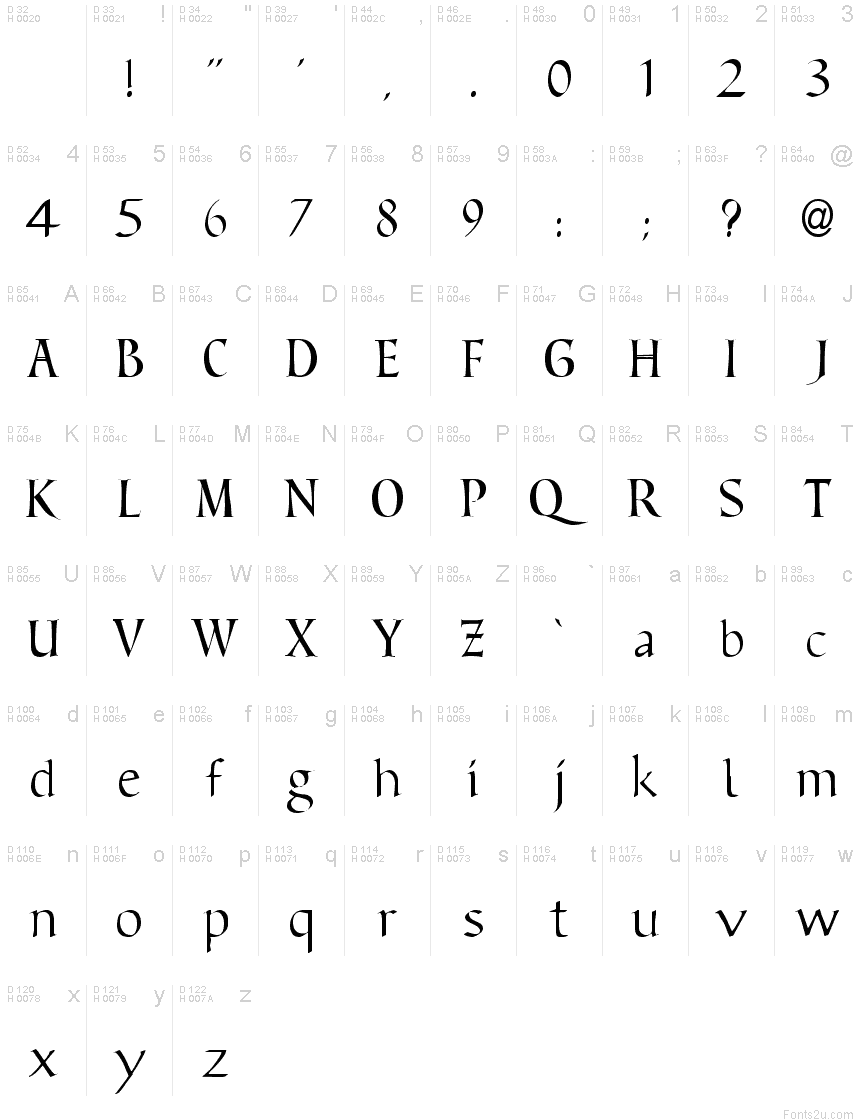
Krój Benevento autorstwa Davida F. Nallego to darmowy, szeryfowy font w stylu retro. Wyróżnia go atramentowy klimat rodem z dawnych książek: masywne pociągnięcia, ostre, wyraziste serify i miękkie łuki sprawiają, że napis wygląda, jakby został wyrzeźbiony w starym szyldzie lub odciśnięty na papierze. Rytm jest żywy i lekko zawadiacki, więc nawet krótkie nagłówki nabierają dzięki niemu charakteru.
Benevento świetnie sprawdzi się na plakatach, okładkach książek, logotypach vintage, etykietach produktów rzemieślniczych, ulotkach, grafikach do podcastów czy szyldach sklepowych. Ten darmowy font potrzebuje oddechu, więc ustaw go nieco większym i nie zagęszczaj interlinii. W podtytułach zestaw go z czystym, oszczędnym krojem bezszeryfowym, aby nie przytłoczyć retro estetyki.